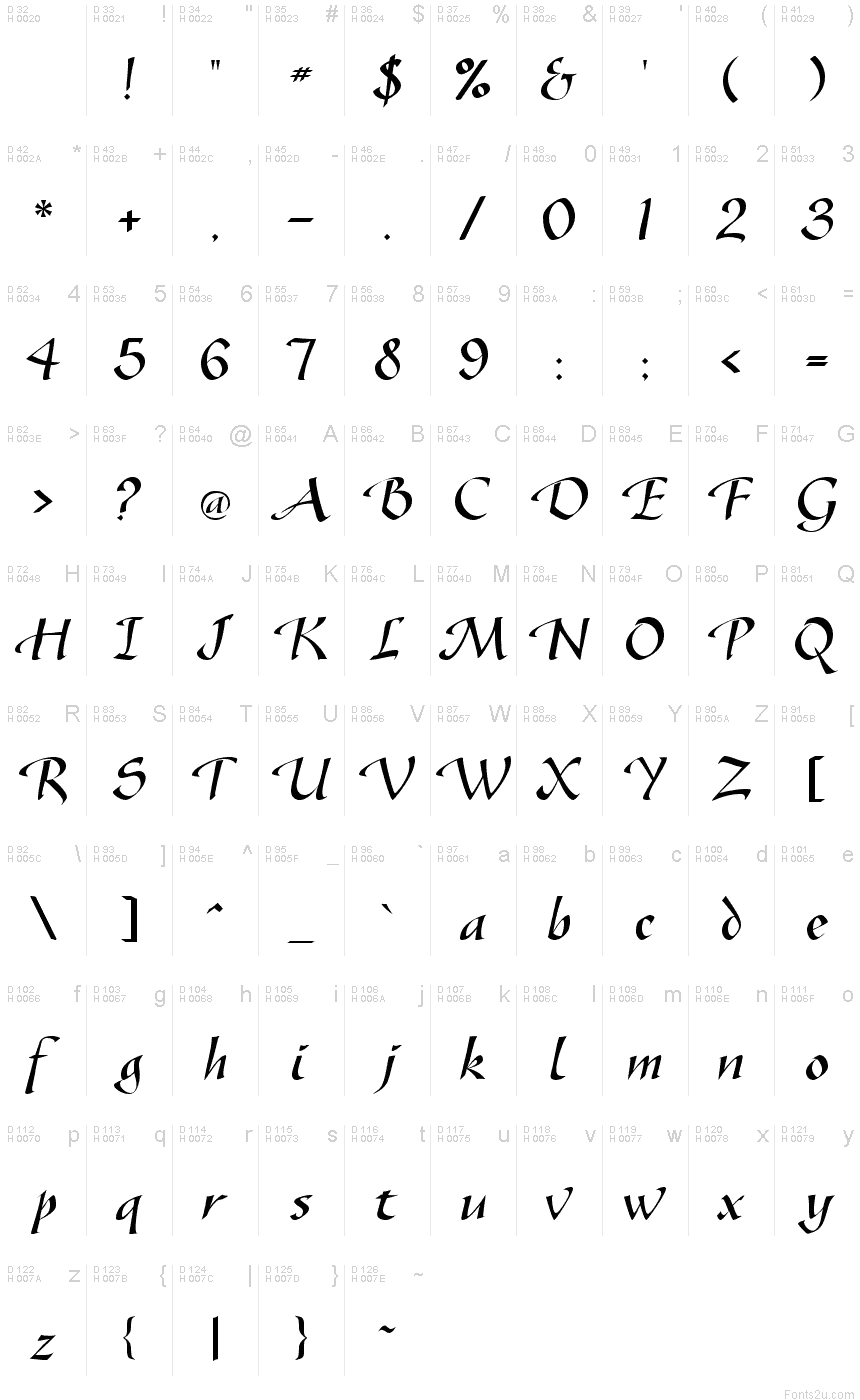
Sonyanna Script SSi je bezplatné kaligrafické písmo od společnosti Southern Software, Inc. Jeho písmena se přiklánějí k ostrému, formálnímu rukopisu s nezaměnitelným digitálním nádechem 90. let. Tento styl se projevuje v rozmáchlých křivkách, ostrých zužujících se tazích a lehce dramatickém rytmu, který dodává slovům ceremoniální, ručně psaný vzhled – na rozdíl od ležérních štětcových stylů.
Toto bezplatné písmo se hodí na pozvánky, blahopřání, branding butiků, obaly kosmetiky nebo menu restaurací, kde špetka formálnosti pomůže nastavit ten správný tón. Funguje také skvěle pro krátké titulky, obálky a monogramy, protože úhlové tahy a zakulacené konce dodávají i několika málo písmenům dostatečnou výraznost, aby dokázala podržet celý vizuál.